타이포 브랜딩과 퍼포먼스의 경계를 넓혀온 티티서울, 야구장에 울려 퍼질 응원 메시지를 디자인하다! 팬들의 열정이 담긴 응원 메시지가 레터링으로 구현된다면 어떤 모습일까? 디자인 엔터테인먼트 티티서울은 이 질문에 답하기 위해 ‘야구 직관 굿즈 워크숍’을 개최했다. 야구 팬들이 직접 디자인한 레터링 굿즈로 경기장의 뜨거운 분위기를 한층 더 돋우고, 팀 응원에 깊이 몰입할 수 있도록 기획된 프로젝트이다.
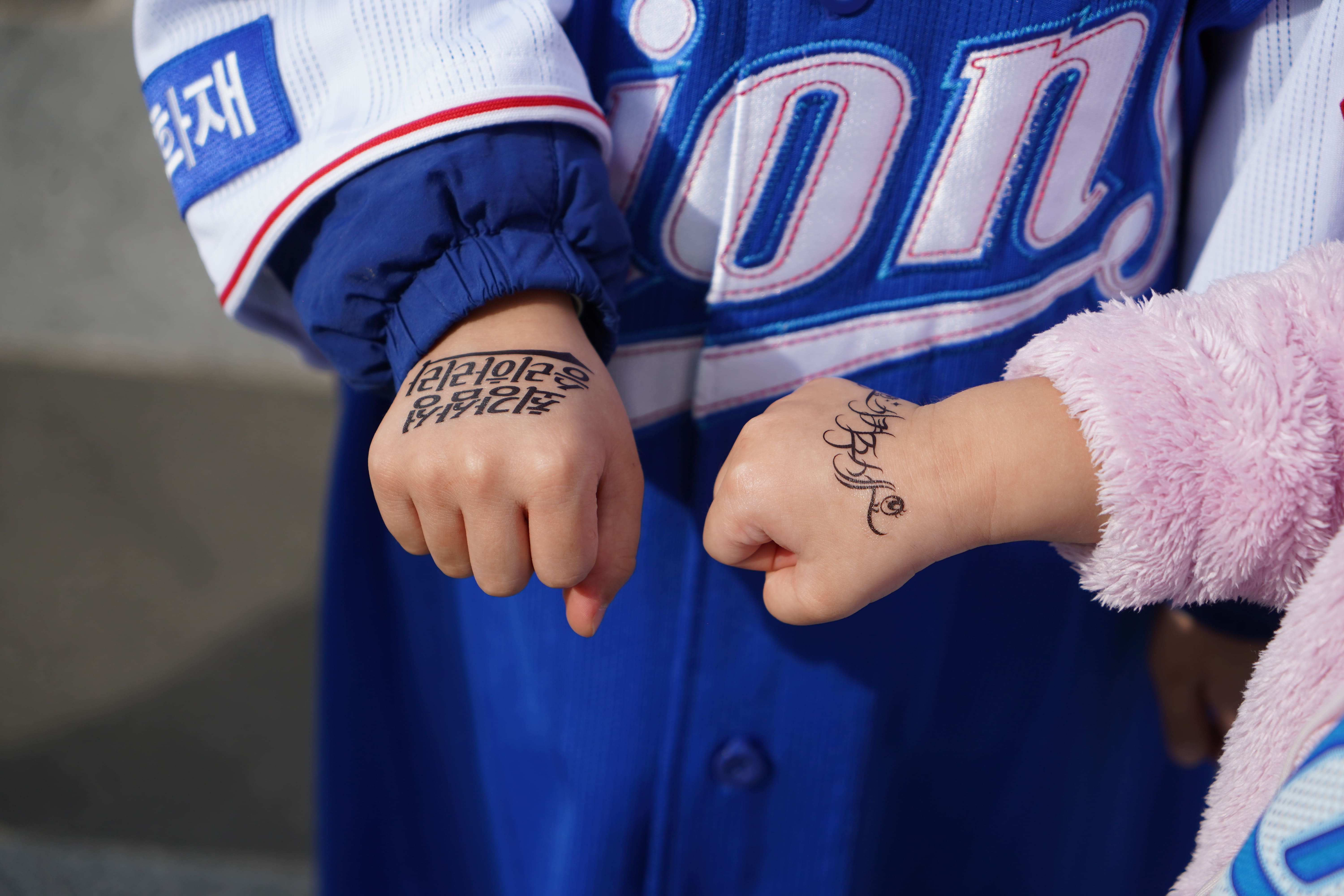
KBO 천만 관중의 비결, 뜨거운 응원 문화
지난해, KBO 리그는 국내 프로 스포츠 역사상 최초로 1000만 관중을 돌파하며 그 인기를 제대로 입증했다. 프로야구 흥행 돌풍의 배경에는 여러 요인이 있지만, 그중에서도 가장 주목받는 것은 한국 야구장만의 독특한 응원 문화였다.
KBO가 지난해 7월 발표한 ‘2024 KBO 관람객 증가 요인 조사 보고서’에 따르면, 구장을 방문한 야구팬 중 43.2%가 가장 기억에 남는 장면으로 ‘응원 문화’를 꼽았다. 단순히 경기를 관람하는 것을 넘어, 목이 터져라 응원가를 부르며 경기에 몰입하는 경험은 KBO 리그만의 특별한 문화로 자리 잡았다. 이런 인기에 힘입어 각 구단은 구단만의 특색을 담은 응원 도구를 제작하고 있다. 팬들은 이 응원 도구를 통해 유대감을 형성하여 응원 문화를 발전시켜 나가고, 더 나아가 직접 응원 도구를 제작하는 팬들도 늘어나고 있다.
디자인 엔터테인먼트 티티서울은 이러한 팬들의 열정을 놓치지 않았다. 팬들이 직접 만든 경기장 굿즈로 더 열정적인 응원을 할 수 있도록 자체 워크숍을 개최하여 10개 구단의 팬들과 함께 굿즈 디자인 작업을 진행했다. 다가오는 2025년 3월 KBO 리그 개막에 앞서, 지난 워크숍의 작업 과정과 그 결과물을 소개한다.
팬심으로 빚어낸 굿즈 디자인
팬들의 열정과 창의력이 담긴 이번 워크숍은 각자의 팀 사랑과 디자인 감각을 표현하는 자리였다.
워크숍은 팬들이 담고 싶은 문구를 정하는 것에서 시작되었다. 이후 선정된 문구 바탕으로 레터링 디자인 작업이 진행되었으며, 멘토와의 1:1 피드백을 통해 작업물의 완성도가 점차 높아졌다.
두산베어스의 팬이자 tt.멤버로 참여한 이희웅은 “좋아하는 팀의 굿즈를 직접 디자인할 수 있다는 점이 정말 매력적이었고, 직접 만든 작업물이 실물로 제작되어 사람들에게 공유되는 경험이 매우 뜻깊었다”며 소감을 전했다. 팬들의 애정과 아이디어가 담긴 직관 굿즈는 경기장에서 응원의 열기를 더하며 팬과 야구를 더욱 가까이 연결했다.
멤버들의 작업물 리뷰
1. tt.멤버 최수빈의 ‘승요시켜주세요’
처음 야구장 직관을 갔을 때, 제가 응원하는 팀이 이겼어요. 그때 ‘혹시 나… 승리 요정일지도?’라는 생각이 들었답니다. 직관을 갈 때마다 모두가 응원하는 팀의 승리를 간절히 바라잖아요? ‘승요시켜주세요’라는 문장은 이런 두근거림과 간절함이 귀엽게 느껴져 선택하게 되었습니다.
야구장을 떠올리면 관중들이 두 손을 모으고 안타 하나를 바라는 초롱초롱한 모습이 가장 먼저 생각납니다. 그래서 문장에 두 번 등장하는 ‘ㅇ’을 순정 만화 속 눈망울처럼 표현해 보는 재미를 더했습니다. 전반적인 분위기도 로맨스 판타지물과 어릴 적 즐겨 보던 순정 만화에서 영감을 받아 구성했습니다. ‘승리 요정’이라는 개념 자체가 판타지스럽기도 하니까요!
획의 두께를 방향과 필압에 따라 변주해 얇았다가 두꺼워지도록 만들어 시각적 재미를 주었고, 글자마다 이어지는 획은 로맨스 판타지 특유의 고풍스러운 느낌을 의도했습니다. 야구장의 강하고 거친 분위기와는 대비되는 귀여운 레터링을 통해 관중들이 미소 지을 수 있는 작은 포인트를 만들어 보고 싶었습니다. 야구장 한편에서 이 귀여운 문구가 누군가의 마음을 살짝 간질이는 순간이 생긴다면, 제 작업은 충분히 성공했다고 생각해요!
2. tt.멤버 이희웅의 ‘공을 네모 안에 넣어’
스트라이크존이라는 네모난 영역에 투수가 공을 잘 넣지 못하자, 한 팬이 ‘공을 네모 안에 넣어’라고 써서 보여줬던 게 기원이 된 밈이예요. 이 밈을 표현하기 위해 레터링 작업에서는 공을 동그랗게, 스트라이크존은 네모로 단순화했어요. 또, ‘안에 넣는다’는 의미를 더 직관적으로 전달하기 위해 공이 들어가는 화살표 모양을 추가하며 디자인을 재구성했습니다.
3. tt.멤버 양하진의 ‘오늘 지면 같이 죽자‘
우선, 저는 웃긴 문구를 만들고 싶었어요. 그래서 야구와 관련된 밈이나 유머를 찾아보던 중 이 문구를 발견했죠. 선수들에게 던지는 격렬한 멘트를 더욱 유머러스하게 전달하기 위해, 과격한 느낌의 투박한 글씨로 야구 팬덤의 열정을 표현했습니다. 추가로 글자 속 공간 곳곳에 야구를 상징하는 요소들을 담아 디자인을 완성했습니다.
당시 현장의 비하인드 스토리를 살짝 말씀드리자면 삼성 팬 한 분이랑 기아 팬 세 분이 계셨는데 “우리 다 똑같이 이거 붙이고 누가 죽는지 한번 봐 보자!”라고 얘기를 나누셨던 기억이 납니다. 당시 경기장에서도 호응이 좋았던 레터링이었어요.
4. tt.멤버 백지웅의 ‘혹시 몰라, 역전할지도!!’
한국시리즈가 시작되고 끝날 때 폭죽이 터지잖아요? 그 순간마다 경기가 주는 긴장감과 희망적인 느낌을 많이 받았어요. 그래서 ‘희망’이라는 키워드를 바탕으로 불꽃놀이에서 느껴지는 동세나 곡선, 또는 획의 꺾임을 디자인에 반영했습니다. 불꽃놀이의 확산하는 움직임을 표현하면서, 야구공의 실밥 디테일을 더해 야구의 정체성을 담아냈습니다.
5. tt.멘토 서동하의 ‘압-도하라! 기아타이거즈’
제가 중요하게 생각한 건 ‘글자의 틀을 깨고 시각적 한계를 넘는 것’이었어요. 대형 포스터나 디스플레이는 크고 눈에 띄어야 하고, 멀리서도 잘 보이는 것이 중요합니다. 작은 글자나 복잡한 디자인은 답답하게 느껴질 수 있고, 메시지 전달에 한계가 있죠. 그래서 간결하면서도 시선을 사로잡는 디자인을 만들고자 했어요.
네모난 형태의 글자는 익숙해서 가독성이 좋지만, 단순한 형태만으로는 매력이 부족할 수 있기에 사선과 같은 장식 요소를 추가했습니다. ‘압도하라’의 경우, 그 단어가 가진 무겁고 힘 있는 의미를 표현하고자 탱크나 군용 차량의 꺾이는 형태에서 영감을 받아 디자인했어요. 이러한 요소들을 조합해 경기장처럼 넓은 공간에서도 강한 인상을 줄 수 있는 디자인을 완성했습니다.
6. tt.멤버 김은수의 ‘롯데가 이겨야 집안이 조용하다’
가족과 친구들이 롯데의 열혈 팬이라 사직구장에서 직관한 경험이 몇 번 있습니다. 그곳에서 항상 눈에 띄었던 건, 깃발을 흔드는 ‘깃발 아저씨’와 그 깃발에 적힌 “롯데가 이겨야 집구석이 조용하다”라는 문구였어요.
이 문구에서 영감을 받아, 이번 작업에서는 롯데 팬들이 공감할 수 있는 문구를 담아봤습니다. 깃발 아저씨의 슬로건을 살짝 변형해, “롯데가 이겨야 집안이 조용하다”라는 문구를 사용했죠. ‘집구석’이라는 표현 대신 ‘집안’으로 순화해 강한 느낌을 줄이고, 디자인은 부드럽고 귀여운 분위기로 조화를 이루려 했습니다.
제 레터링이 좋은 기운을 전해, 내년에는 롯데가 좋은 성적을 거두길 바라며 외쳐봅니다. 롯데 화이팅!
7. tt.멤버 황서영의 ‘도영아 니 땜시 살어야’
저는 이번 작업 기간이 마침 한국시리즈 시즌이라 많은 팬들에게 즐거움을 주고 싶었어요. 그래서 기아 타이거즈 김도영 선수를 주제로 “도영아, 너 땜시 살어야”라는 슬로건을 제작해 봤습니다. 김도영 선수의 귀여운 매력을 담기 위해 귀엽고 재치 있게 디자인했고, 타이거즈를 상징하는 호랑이 무늬랑 캐릭터를 더해 슬로건을 완성했습니다.
제가 만든 야구 레터링이 많은 관중들에게 관심을 받고, 좋은 추억이 되었다는 게 정말 뿌듯했어요. 좋아하는 야구를 주제로 처음 레터링 작업을 해본 이번 경험, 정말 뜻깊었습니다.
8. tt.멤버 정예린의 ‘우리가 원하는 건 승리!’
저는 키움 히어로즈의 응원가 중 한 구절인 ‘우리가 원하는 건 승리!’라는 문구로 레터링 작업을 진행했습니다. 처음 직관한 경기에서 이 응원가를 따라 부르던 감동이 아직도 생생해서, 이 문구를 작업 주제로 선택하게 됐습니다.
이번 작업의 목표는 깔끔하고 한눈에 잘 들어오는 레터링을 만드는 것이었어요. 승리에 대한 의지를 표현하기 위해 볼드한 고딕체로 문구를 강조하고, 커팅 요소를 추가해 선수들의 날카로운 집중력과 승리 열망을 상징적으로 담아냈습니다. 단순하지만 강렬한 느낌을 주고 싶었죠. 이 레터링으로 한 구단의 팬으로서 선수만큼이나 간절히 승리를 바라는 팬들의 마음을 잘 표현하고 싶었습니다.
9. tt.멤버 도예나의 ‘최강삼성 승리하리라’
저는 ‘최강 삼성 승리하리라’라는 문구를 선택했습니다. 처음 삼성 직관을 갔을 때, 응원 문화가 이렇게 성대하고 체계적이라는 사실에 놀랐고, 직관이 주는 매력을 실감했어요. 특히 8회 초가 끝난 뒤 울려 퍼지는 응원가 ’엘도라도’는 그 압도적인 응원 열기를 강렬히 느끼게 해줬습니다. 그래서 이 응원가의 메인 가사인 ‘최강 삼성 승리하리라’를 레터링 작업의 텍스트로 선택했습니다.
이 문구는 삼성 라이온즈 온라인 굿즈샵에서도 슬로건 타올에 사용되고 있지만, 직관성과 디자인 면에서 조금 아쉬움이 느껴졌습니다. 이를 보완하기 위해 삼성의 상징색을 더 부각시키면서도 깔끔하고 세련된 디자인을 담으려고 노력했습니다. 삼성 라이온즈 엠블럼을 참고해 레터링을 구성했으며, ‘최강 삼성’은 상대적으로 굵은 서체로 강조했습니다. ‘승리하리라’는 엠블럼의 ‘Lions’ 하단 그래픽에서 착안해 마지막 글자인 ‘라’와 자연스럽게 연결되도록 디자인했습니다.
10. tt.멤버 김한별의 ‘미치도록 사랑한다! 최강기아’
제가 선택한 문장은 “미치도록 사랑한다! 최강 기아”입니다. 이 문장에서 느껴지는 열정과 에너지를 디자인에 녹여내고자 했습니다.
먼저, ‘미치도록 사랑한다!’는 기아 팬들의 뜨거운 팬심을 강조하기 위해 활활 타오르는 불의 형상을 활용했습니다. 이는 기아 팬들의 열정을 상징적으로 표현합니다. 반면, “최강 기아”는 기아의 마스코트인 호랑이의 날카로운 이빨을 형상화해 강렬한 이미지를 전달하고자 했습니다. 두 문구를 구분 짓기 위해 ‘미치도록 사랑한다!’는 심플한 디자인으로 진행하고, 불의 형상을 제외하는 대신 기아 로고의 요소를 활용하여 날카로운 느낌을 살렸습니다.
컬러는 기아를 상징하는 레드 컬러를 중심으로 화이트와 진청색을 조화롭게 사용했습니다. 이 색 조합으로 불꽃을 떠올리게 하고, 레터링에 생동감을 더해줬습니다. 팬들의 열정을 담아낸 이번 작업이 기아 팬들의 마음에 깊이 와닿길 바랍니다!
덕업일치의 최종장, KBO 한국시리즈 현장 굿즈 배포!
이번 워크숍 결과물은 지난 10월 26일, 한국시리즈 4차전이 열린 대구 라이온즈파크 경기장에 배포되었다.
경기장을 찾은 관중들은 멤버들의 굿즈를 통해 경기에 더욱 몰입할 수 있었고, 멤버들은 자신이 직접 만든 디자인이 현장에서 사용되는 모습을 보며 레터링 디자인의 영향력을 체감했다.
완성도 높은 디자인은 메시지 전달의 도구를 넘어, 메시지에 힘과 설득력을 부여하여 더 깊은 공감을 이끌어낸다. 이번 워크숍은 그 예시를 잘 보여준 자리로 디자인과 메시지의 조화가 어떻게 응원 문화를 풍성하게 만드는지 여실히 보여주었다.